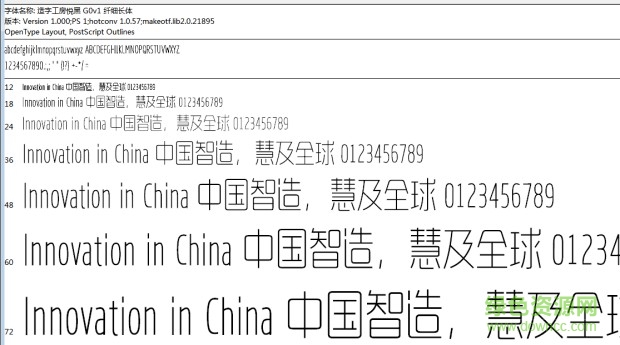
造字工房悅黑纖細(xì)長(zhǎng)體字體是一款非常時(shí)尚又非常實(shí)用的字體,這款字體屬于造字工房中的一種,字體非常纖細(xì)又長(zhǎng),有喜歡的朋友就來(lái)綠色資源網(wǎng)下載吧!
造字工房悅黑纖細(xì)長(zhǎng)體是一款極具個(gè)性的字體,改字體粗細(xì)得當(dāng),彰顯了自己的個(gè)性。